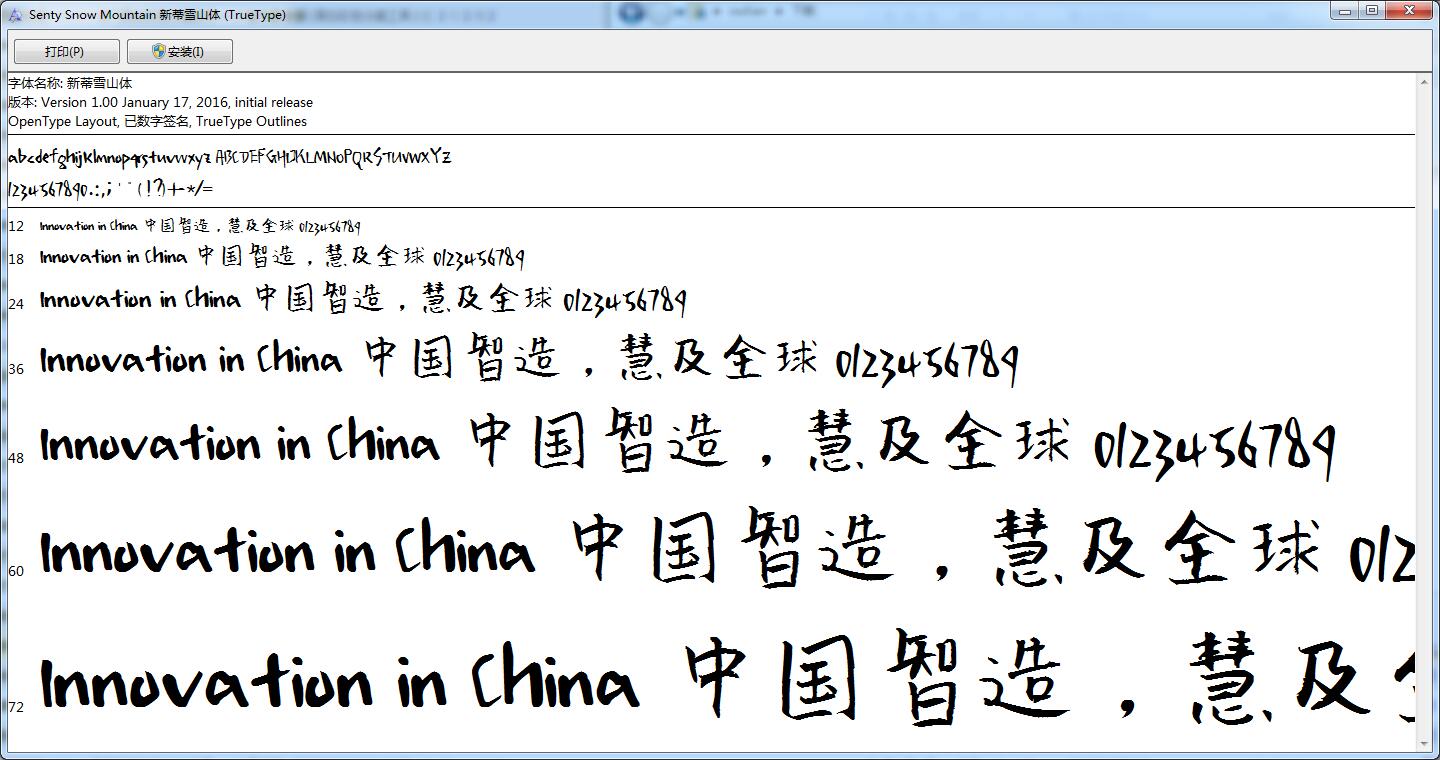
新蒂雪山體
新蒂雪山體是一款卡通風(fēng)格的字體應(yīng)用。覆蓋常用簡體、繁體漢字拉丁字母、數(shù)字。可以適用于多個行業(yè)領(lǐng)域!需要的用戶可以來綠色資源網(wǎng)下載使用!
新蒂雪山體(SentySnowMountain)是一款用于美工設(shè)計方面的中文字體,該字體屬于卡通風(fēng)格,筆畫細膩柔美,且字體完整,整體效果十分出眾,能夠適用于包裝印刷、廣告設(shè)計、平面設(shè)計、書籍報紙等領(lǐng)域。喜歡這款字體的用戶歡迎在綠色資源網(wǎng)下載使用!